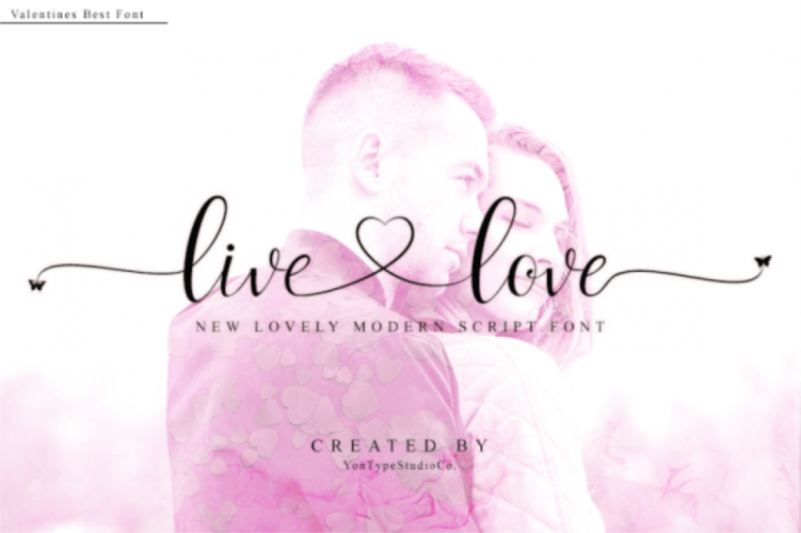
Live Love Calligraphy Font – Fonte Grátis
Live Love Calligraphy Font
Introduzimos a fonte Live Love Calligraphy, uma tipografia escrita à mão com textura limpa e elegante. Esta fonte é perfeita para invitations de casamento, logotipos e identidade visual. A fonte inclui letras maiúsculas e minúsculas completas, junto com as pontuação completa. Além disso, a fonte traz várias características de ganchos que são inovadoras e muito únicas, com um aspecto encantador e delicado. Quer saber o que você está adquirindo, minha querida? Você obterá uma tipografia perfeitamente adequada para eventos importantes, como invitations de casamento ou logotipos de negócios. Essa fonte também é altamente adaptável a múltiplas línguas. Além disso, o design da fonte inclui várias variações de ganchos que garantem uma identidade visual única e chamativa. É perfeita para quando você deseja transmitir um sentimento leve e encantador em seus projetos visuais.